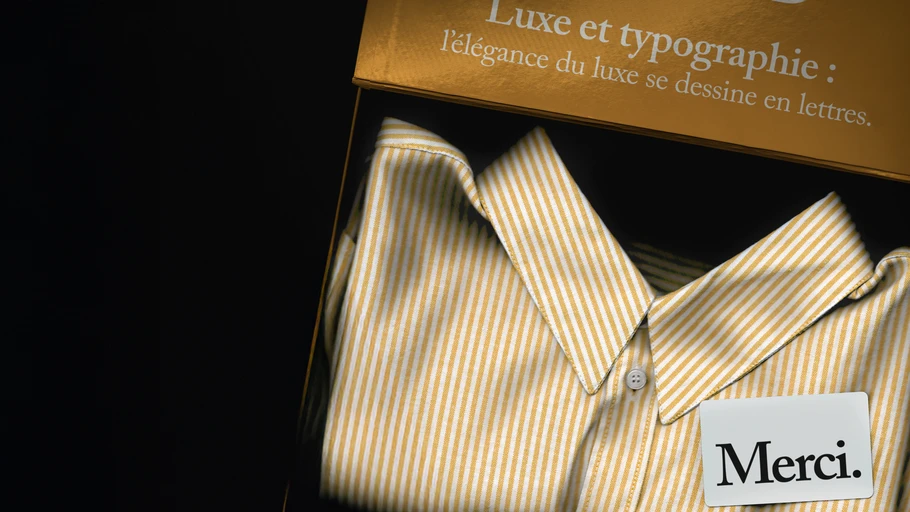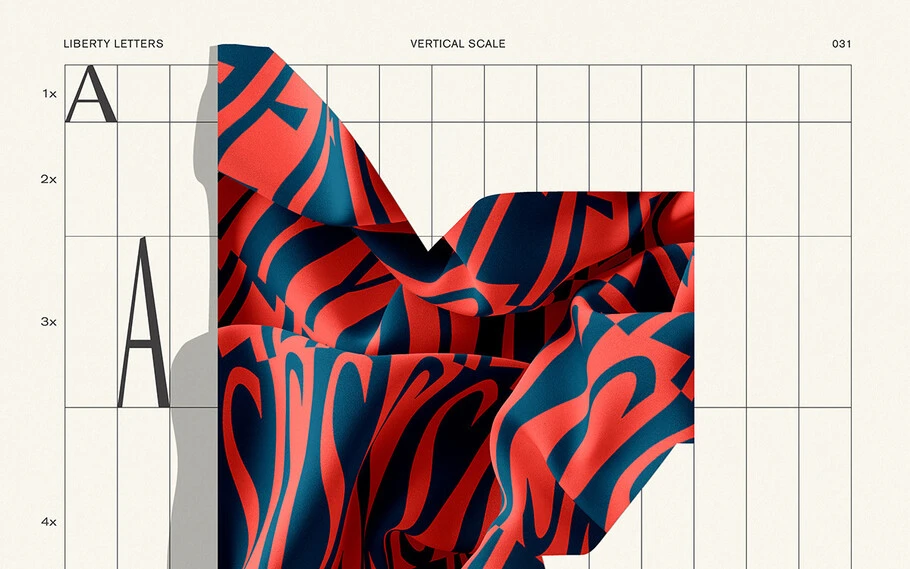
Luxe et typographie : l'élégance du luxe se dessine en lettres
Certaines marques se distinguent instantanément grâce à leur identité visuelle. Les carreaux iconiques de Burberry, le logo entrelacé de Gucci ou encore les valises monogrammées de Louis Vuitton sont des exemples parfaits de codes visuels devenus intemporels.
La typographie, élément graphique central dans le luxe
Les polices de caractères ou le design des logos choisis par les grandes maisons ne sont jamais anodins : ils incarnent leurs valeurs, leur histoire et leur vision tout en traduisant leur positionnement stratégique.
Les normes visuelles du luxe sont souvent subtiles et codifiées : elles évoquent l’élégance intemporelle, la sophistication et l’exclusivité. Cependant, ces codes évoluent au fil du temps, sous l’influence des tendances graphiques et des attentes changeantes du public.
Prenons l’exemple des logos géométriques sans empattement, qui ont connu une forte popularité ces dernières années. Des marques comme Burberry, ont adopté cette simplification avant de revenir récemment à leur logo d’origine, témoignant d’une volonté de renouer avec leur patrimoine tout en répondant aux modes. Ces allers-retours entre modernité et tradition illustrent l’importance de rester pertinent, en vogue, tout en affirmant son unicité.
Dans cet univers, se démarquer visuellement est essentiel. Chaque élément, du lettrage au logo, doit véhiculer un ADN fort et différenciant. Une identité visuelle qui manque de singularité risque de diluer l’impact de la marque. Les grandes maisons de luxe le savent : la différence n’est pas seulement un avantage, elle est une nécessité pour exister dans un marché saturé.
Hermès : l’équilibre entre tradition et modernité
Commençons par la maison Hermès, qui illustre parfaitement comment le lettrage et l’identité visuelle s’intègrent dans une stratégie globale. Son logo, introduit dans les années 1950, puise son inspiration dans le tableau d’Alfred de Dreux, Le Duc attelé, groom à l’attente. Ce logo raconte une histoire, reprenant les origines équestres d’Hermès à travers le carrosse et le cheval, symboles de l’artisanat et du luxe aristocratique.
Côté lettrage, Hermès a opté pour une approche sobre et élégante : des lettres épurées qui incarnent un équilibre entre tradition et modernité. Bien que la marque ait utilisé Memphis Bold dans son histoire graphique, on retrouve aujourd’hui sur son site des typographies comme Orator et Helvetica, renforçant un style intemporel et universel.
Le logo s’inscrit dans un système visuel harmonieux, complété par l’emblématique boîte orange à bords marron. Cette esthétique intemporelle a d’ailleurs valu à Hermès un Oscar du meilleur packaging en 1994. Aujourd’hui, la maison va encore plus loin en intégrant l’éco-conception dans ses packagings, témoignant d’un engagement à conjuguer luxe et responsabilité environnementale.
Devanture d'un magasin Hermès
Nouveau Logo Bugatti
Le luxe progressiste de Bugatti
Parmi les marques ayant récemment brillé pour leur identité visuelle, Bugatti se distingue particulièrement. La célèbre maison automobile a entièrement repensé son identité graphique, adoptant un design épuré qui traduit son ADN d’innovation et de performance.
L’introduction d’une nouvelle typographie épurée, inspirée des anciennes plaques de rue françaises et des archives photographiques de la marque ; créée par le typographe Thomas Huot-Marchand. Un logo très puissant aux empattements marqués avec un E inversé, évoquant les initiales du fondateur. Une nouvelle palette de bleus Bugatti, ainsi qu’une nouvelle direction photographique a permis à Bugatti de renforcer son image de luxe technologique et intemporel. Ce travail réalisé par l’agence Interbrand a été couronné de succès : la marque a reçu le prestigieux Red Dot Design Award, un prix qui souligne l’excellence du design dans tous ses aspects.
Cet exemple illustre comment une identité visuelle soigneusement pensée peut propulser une marque en véhiculant des valeurs fortes et visant un positionnement hyper-luxe.
Hermès, Bugatti ou Burberry montrent que le luxe, même lorsqu’il adopte les tendances, ne sacrifie jamais sa singularité. Ces marques prouvent que l’équilibre entre innovation et héritage est la clé pour rester pertinent tout en cultivant l’intemporalité.
L’impact émotionnel des choix typographiques
Dans l’univers du luxe, l’identité de marque repose sur une orchestration minutieuse où chaque détail visuel et narratif joue un rôle clé dans la connexion émotionnelle avec le consommateur. Les choix typographiques, influencent profondément la manière dont les marques communiquent leurs valeurs d’exclusivité, d’élégance intemporelle et d’innovation.
Une étude menée conjointement par Monotype et Neurons en 2021-2022 a démontré que la typographie agit comme un levier stratégique dans la perception des marques, affectant directement des attributs clés tels que la confiance, la qualité perçue et l’innovation.
Héritage et sophistication : polices classiques à empattements
Les polices à empattement, comme Cotford Display Regular, incarnent une esthétique qui puise dans les modèles classiques tels que Caslon ou Baskerville. Ces polices, souvent associées à des industries comme la mode, le luxe ou l’édition, évoquent un sérieux et une sophistication intemporelle. Dans l’étude, ce type de typographie a été corrélé à une augmentation de 13 % de la perception de qualité et de 9 % de la fiabilité. Cet impact découle de leur association culturelle à l’élégance traditionnelle et à l’excellence artisanale. Des marques comme Hermès, s’appuient sur ces codes visuels pour tisser un lien fort entre héritage et innovation.
Modernité et authenticité : polices sans sérifs
À l’autre extrémité du spectre, les polices sans serif humanistes, telles que FS Jack, inspirées par la calligraphie, se distinguent par leur capacité à renforcer des attributs comme l’authenticité et la proximité. Ces typographies augmentent la perception d’innovation de 9 % et renforcent des valeurs telles que la sincérité (+10 %) et l’honnêteté (+5 %). Grâce à leur équilibre entre modernité et humanité, elles permettent aux marques de forger une connexion émotionnelle sincère avec leur audience, tout en cultivant un sentiment d’appartenance durable.
Les polices sans serif géométriques, telles que Gilroy Bold, jouent un rôle prépondérant dans le domaine publicitaire et digital. Leur simplicité et leur lisibilité augmentent la mémorabilité des messages de 6 % et améliorent l’avantage concurrentiel perçu de 12 %. Avec leur esthétique minimaliste et fonctionnelle, ces typographies véhiculent une modernité captivante, idéale pour des slogans ou des campagnes visuelles visant à projeter une image d’innovation et de dynamisme.
Le jeu du désir : éditions limitées et collaborations inédites
Au-delà de l’identité visuelle, la désirabilité des marques de luxe repose sur leur capacité à rendre l’inaccessible tangible à travers des collaborations uniques et des éditions limitées.
Prenons l’exemple de Dior, qui a fait appel à la fonderie Violaine & Jérémy pour la création d’une typographie sur mesure, utilisée dans sa collection de foulards Mitzah. Ce caractère typographique raffiné reflète la sophistication de la maison, fusionnant élégance intemporelle et touche contemporaine pour enrichir l’univers visuel de ses textiles de soie.
De même, Liberty Fabrics, en collaboration avec l’agence Pentagram et Colophon Foundry, a réinterprété son héritage typographique. Ensemble, ils ont conçu Lazenby Sans, une police inspirée des enseignes historiques de la boutique sur Great Marlborough Street. Utilisée pour des motifs kaléidoscopiques audacieux, elle allie tradition et modernité, incarnant l’esprit excentrique de la marque à travers une fusion de patrimoine et de technologie.
Ces collaborations transforment l’acte d’achat en une expérience sensorielle et émotionnelle. Chaque produit devient un fragment d’un univers idéalisé, où l’objet se mue en totem de désirabilité et d’appartenance.
Pentagram en collaboration avec Colophon Foundry : Lasenby Sans
Récits intemporels, créateurs d’émotions
L’identité visuelle incarne l’âme du luxe, un fil invisible qui relie tradition et modernité. À travers des choix typographiques subtils, des codes graphiques intemporels et des collaborations audacieuses, les maisons de luxe parviennent à inscrire leur unicité dans l’éternité.
Dans un univers saturé, où chaque image se mêle à une autre, ces marques rappellent avec éclat que se distinguer est une nécessité vitale. Ce ne sont pas seulement des produits qu’elles offrent, mais des histoires à vivre, des émotions à ressentir, et des rêves à partager. C’est dans ces récits, faits de désir et d’appartenance, que réside la magie du luxe.